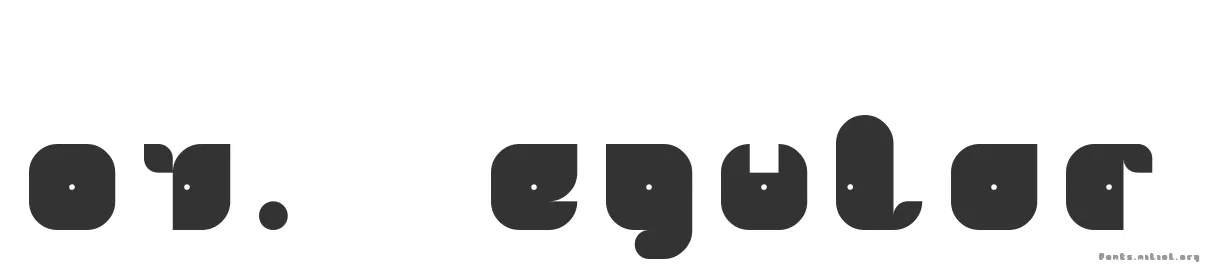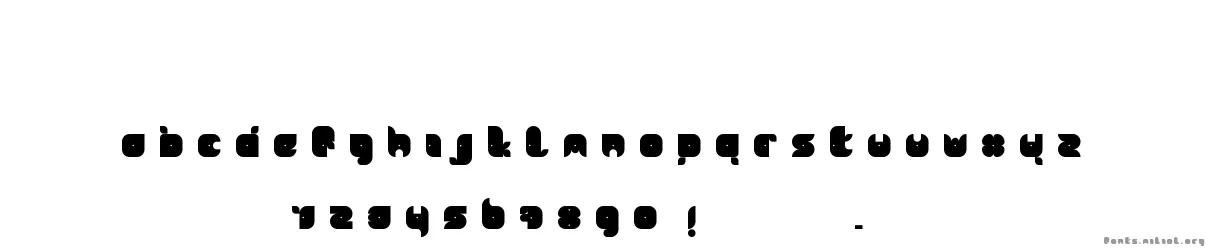
01.BASE Regular (01.BASE) 字体下载
## 01.BASE Regular:极简主义美学的字体呈现
01.BASE Regular是一款极具现代感的无衬线字体,其设计理念源于极简主义美学。这款字体以几何形状为基础,通过精确的线条和均匀的笔画,呈现出干净利落的视觉效果。
字体的每个字母都经过精心设计,确保在保持统一性的同时,每个字符都具有独特的识别性。01.BASE Regular的字母间距经过科学计算,既保证了阅读的流畅性,又维持了整体的视觉平衡。这种设计使得字体在各类数字界面和印刷品中都能保持出色的可读性。
在数字时代,01.BASE Regular的简约风格完美契合现代设计需求。其清晰的线条和规整的结构,使字体在小字号显示时依然保持清晰,在大字号使用时则展现出强烈的视觉冲击力。这种特性使其成为网页设计、移动应用界面和品牌标识的理想选择。
01.BASE Regular的设计体现了功能性与美学的完美结合。它不仅仅是文字的载体,更是一种视觉语言的表达。这款字体通过其独特的设计语言,为现代设计提供了新的可能性,展现了极简主义在字体设计领域的创新应用。